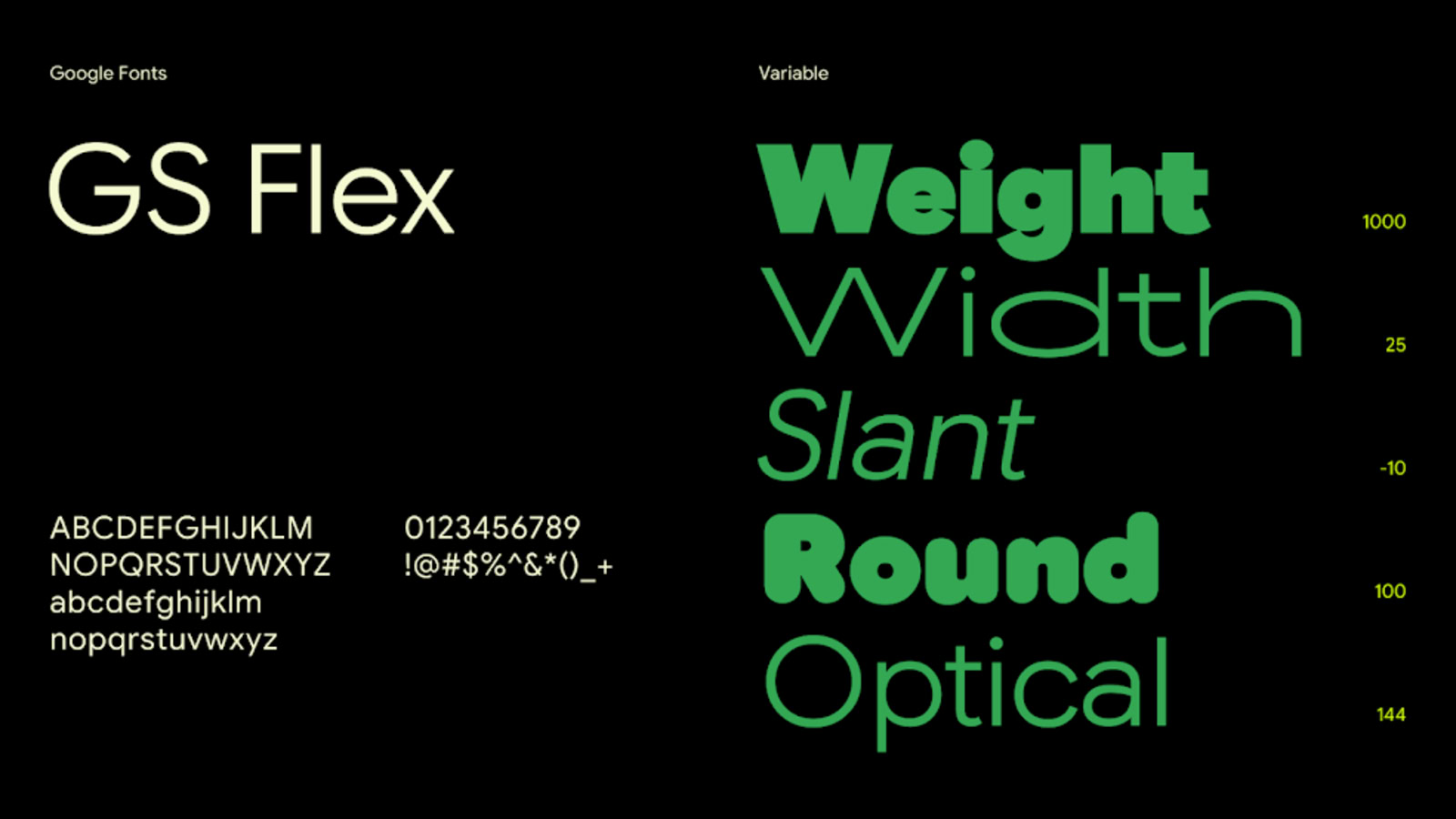
La recente introduzione del font Sans Flex da parte di Google rappresenta un’importante novità nel campo della tipografia. Questo carattere, che si distingue per la sua grande flessibilità, è ora disponibile per il download gratuito, consentendo a designer e sviluppatori di utilizzarlo nei loro progetti.
Google rilascia il font Sans Flex al pubblico
Sans Flex è definito come la “prossima generazione del carattere brand di Google”. Può essere scaricato dal sito di Google Fonts ed è classificato come un font variabile estremamente versatile, dotato di cinque assi variabili: peso, grado, inclinazione, larghezza e rotondità. Questa tipologia di font funge anche da base per la variante “Rounded” utilizzata nel linguaggio di design Material 3 Expressive, lanciato nel 2023.
Un post sul blog di Google Design del 2024 dedicato alla tipografia variabile mette in evidenza la flessibilità del font. Casey Henry, designer dell’azienda, sottolinea che Google Sans Flex “consente alle forme delle lettere di adattarsi a diverse scale”. L’implementazione degli OpenType Font Variations rappresenta lo standard adottato da Google per i font variabili.